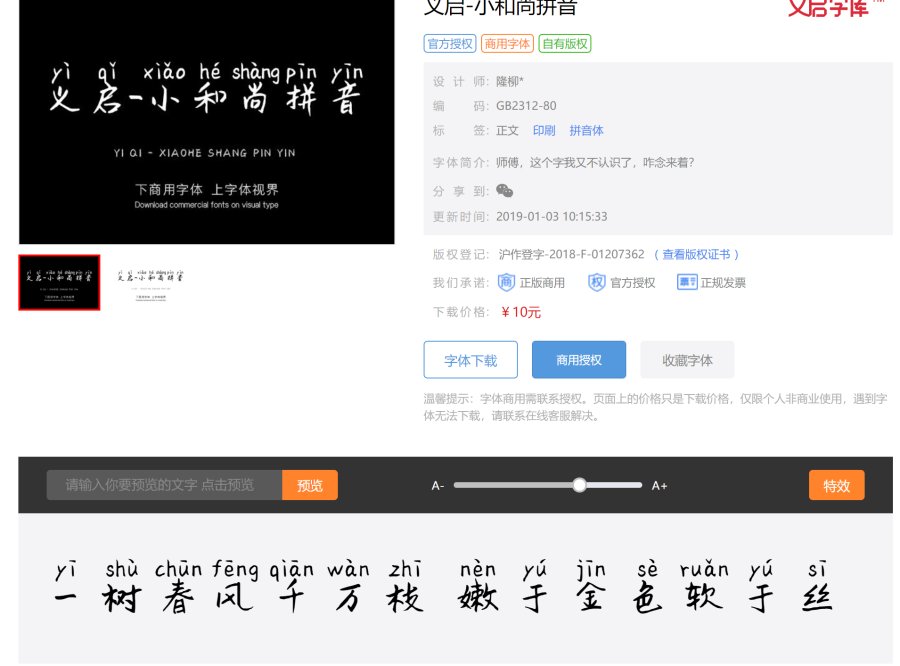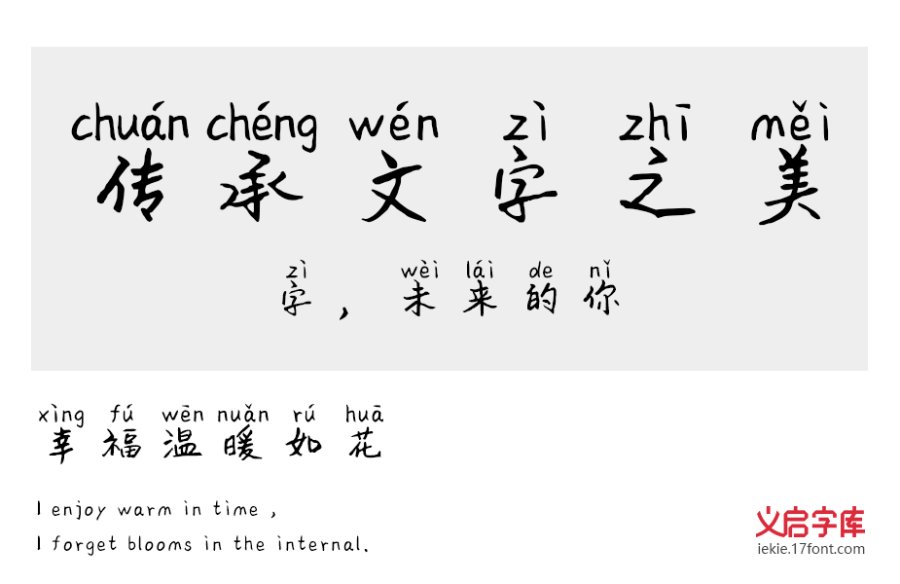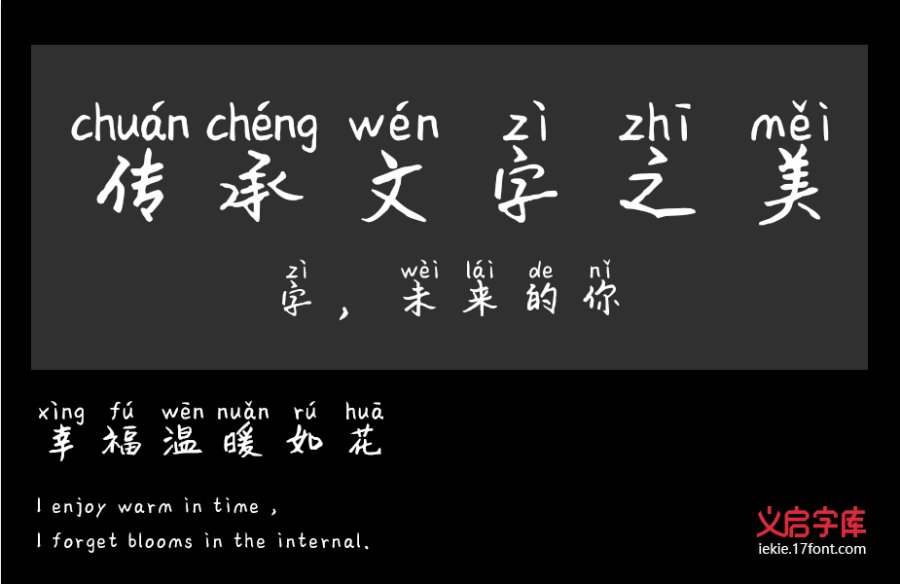
在偏僻的山里,有一位学识渊博的老和尚,他每天都读书、思考。他有一个徒弟——小和尚。小和尚每天都勤恳的挑水做饭洗衣。老和尚亦毫无保留的教小和尚认字明理。老和尚明白授人以鱼不如授人以渔,想要学更多的汉字,就要先学会拼音。所以从平平仄仄开始教学。小和尚也非常认真用心的学习,孜孜不倦、乐此不疲,不会拼的拼音、不识的字常请教师傅。
如老和尚的教学,义启小和尚拼音中有四个声调,即阴平、阳平、上声、去声。有26个汉语拼音字母,声母、韵母、前鼻音、后鼻音、后韵母等现代汉语拼音组成。为小和尚学习生字铺垫了良好的基础,充分体现了我国优良文化的传承。一代传一代,薪火相传,生生不息。
老和尚告诉小和尚,点横撇竖捺构成汉字,形成中国文化。书写汉字横竖交叉先横,撇捺交叉先撇。手还稚嫩的小和尚端正坐姿,拇指食指握笔杆,认真的书写伟大的汉字。
义启小和尚拼音体,字体清新俏皮,线条流畅,给人简洁又不失底蕴的厚实感。字形上不拘直线条风格,流畅的曲线,风格独特,整体和谐统一。钩笔画的该钩则钩,做传统文学,造型规整又不失活泼个性,给人一种清新、开阔的感觉。